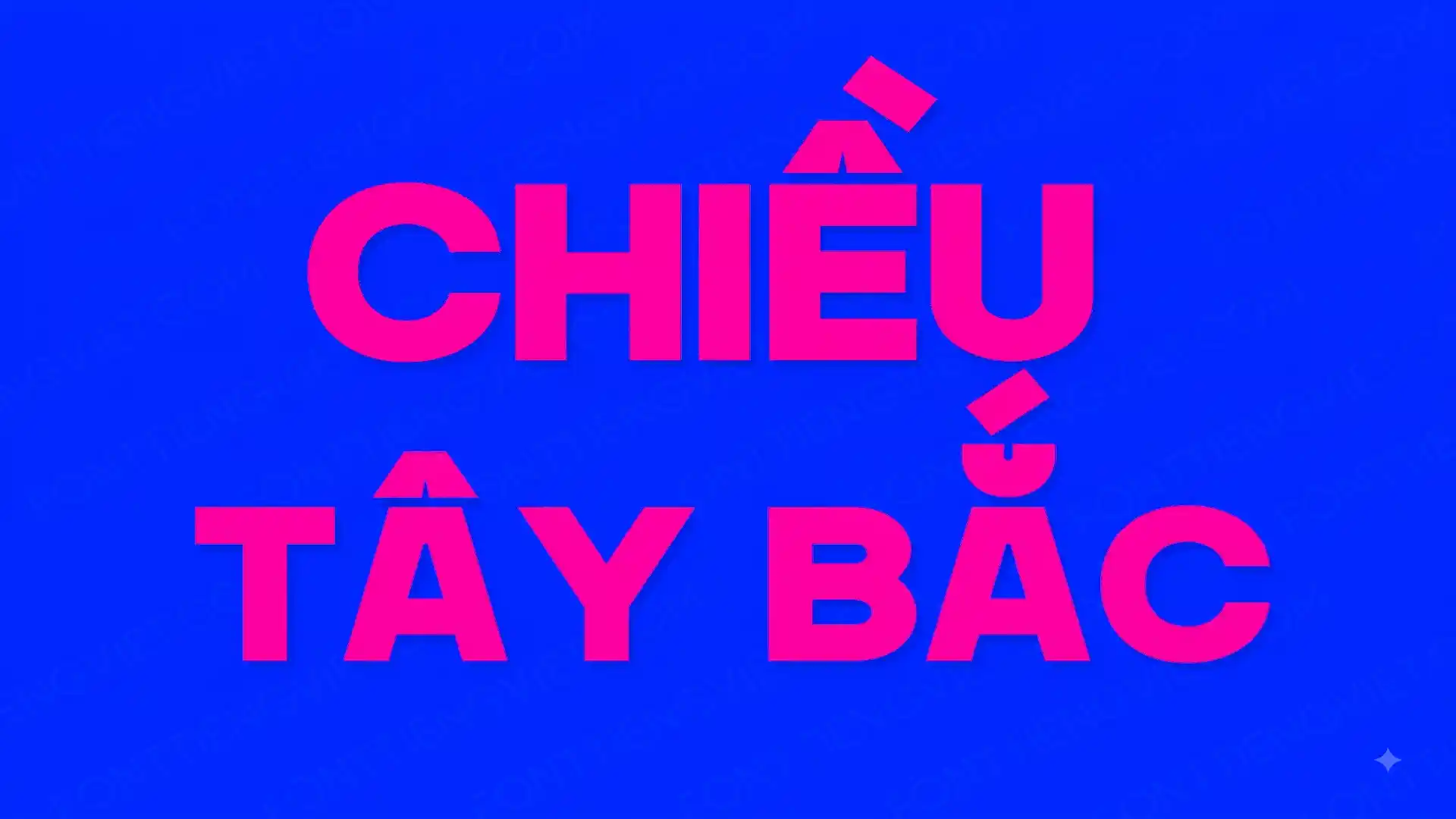
Trong thế giới thiết kế đồ họa, việc lựa chọn một phông chữ phù hợp đóng vai trò quyết định đến sự thành công của toàn bộ ấn phẩm. Nếu bạn đang tìm kiếm một phông chữ mang đậm nét cá tính, mạnh mẽ và đậm chất tương lai (futuristic), thì font Việt hóa 1FTV VIP Neogen Black chính là “mảnh ghép” hoàn hảo mà bạn không thể bỏ qua.
1. Tổng Quan Về Font 1FTV VIP Neogen Black
Neogen là một bộ phông chữ thuộc họ Sans-serif (không chân) nổi tiếng với đường nét cứng cáp, dứt khoát và mang hơi hướm công nghệ. Phiên bản Neogen Black là định dạng có độ dày lớn nhất, giúp tối ưu hóa khả năng hiển thị và thu hút ánh nhìn ngay từ giây phút đầu tiên.
Bản việt hóa mang tên 1FTV VIP Neogen Black được thực hiện bởi đội ngũ 1FTV (1Font Tiếng Việt) với tiêu chuẩn VIP. Điều này đồng nghĩa với việc phông chữ đã được căn chỉnh tỉ mỉ từng dấu câu, khoảng cách (kerning) để phù hợp tuyệt đối với hệ thống bảng chữ cái tiếng Việt.
Phong cách thiết kế Hiện đại, Công nghệ, Khối mảng lớn
2. Ưu Điểm Nổi Bật Của Bản Việt Hóa 1FTV VIP
Không phải ngẫu nhiên mà phiên bản VIP của 1FTV lại được giới designer săn đón. Dưới đây là những lý do khiến font chữ này trở nên đáng giá:
• Dấu tiếng Việt chuẩn xác: Các dấu câu (sắc, huyền, hỏi, ngã, nặng) được vẽ lại và đặt ở vị trí hoàn hảo, không bị vỡ nét hay dính vào nhau kể cả khi bạn thiết kế ở kích thước lớn.
• Kerning tối ưu: Khoảng cách giữa các ký tự có dấu trong tiếng Việt đã được tinh chỉnh lại toàn bộ, mang lại cảm giác mượt mà và chuyên nghiệp khi gõ văn bản dài.
• Tính đa dụng cao: Dù sở hữu đường nét cực dày (Black), font vẫn giữ được sự rõ ràng và sắc nét trên cả màn hình kỹ thuật số lẫn các bản in ấn vật lý.
3. Ứng Dụng Thực Tế Trong Thiết Kế Đồ Họa
Với thiết kế mang phong cách mạnh mẽ và bùng nổ, Font 1FTV VIP Neogen Black đặc biệt phù hợp cho các dự án yêu cầu sự chú ý cao:
• Thiết kế Logo & Typography: Tuyệt vời để làm logo cho các thương hiệu công nghệ, thể thao điện tử (eSports), thời trang streetwear hoặc các dự án startup.
• Poster & Banner quảng cáo: Sử dụng làm tiêu đề (Headline) lớn trên các ấn phẩm truyền thông mạng xã hội, banner sự kiện âm nhạc (EDM, Hip-hop).
• Giao diện UI/UX Game: Thích hợp để làm phông chữ hiển thị cho các tựa game hành động, khoa học viễn tưởng.
• Bao bì sản phẩm: Tạo điểm nhấn ấn tượng, khỏe khoắn cho các sản phẩm dành cho nam giới, đồ uống tăng lực hoặc thiết bị điện tử.